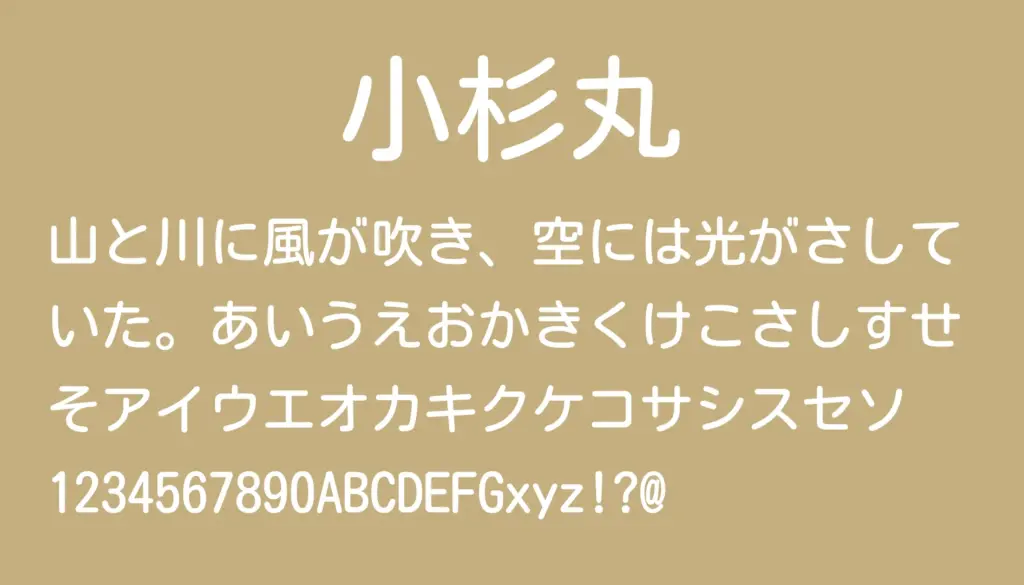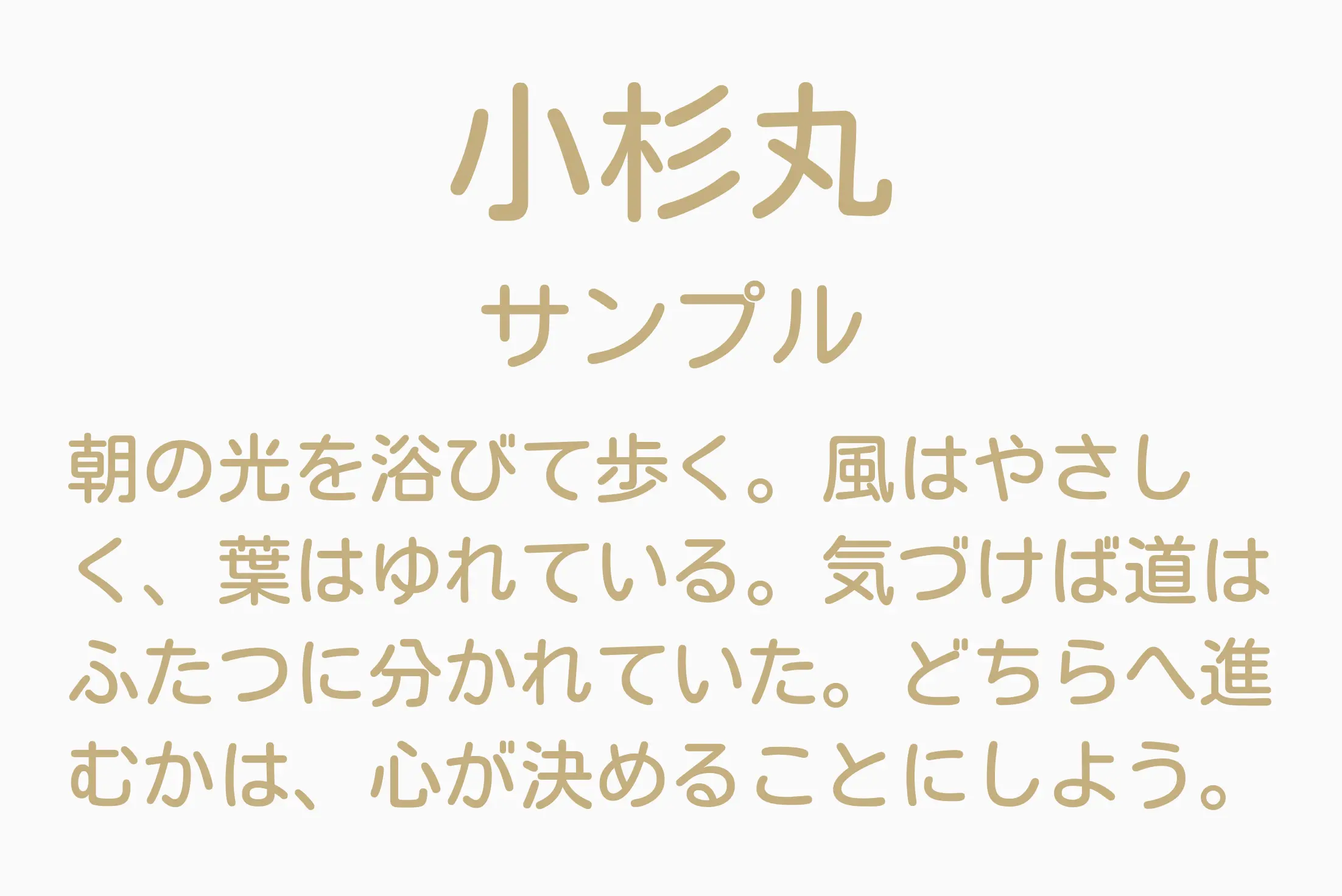
Google Fonts で配布されている 読みやすく親しみやすい丸ゴシック体の日本語フォントです。線の太さは控えめで、クセのない整ったデザインが特徴。長文でも疲れにくい設計となっています。やさしくやわらかな印象がありながらも、可愛くなりすぎないので、ビジネス資料や教育系コンテンツでも安心して使えるフォントです。
小杉丸